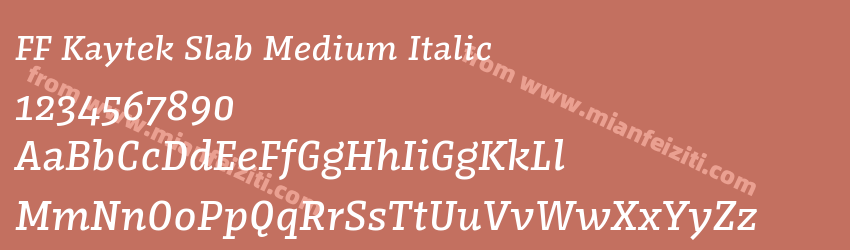
FF Kaytek Slab Medium Italic
字体名称: FF Kaytek Slab Medium Italic
Postscript名称: KaytekSlab-MediumItalic
字体字重: Medium Italic
本款“FF Kaytek Slab Medium Italic”是一款书写很新颖的字体,字体大方,适合各种设计作品使用!欢迎下载!